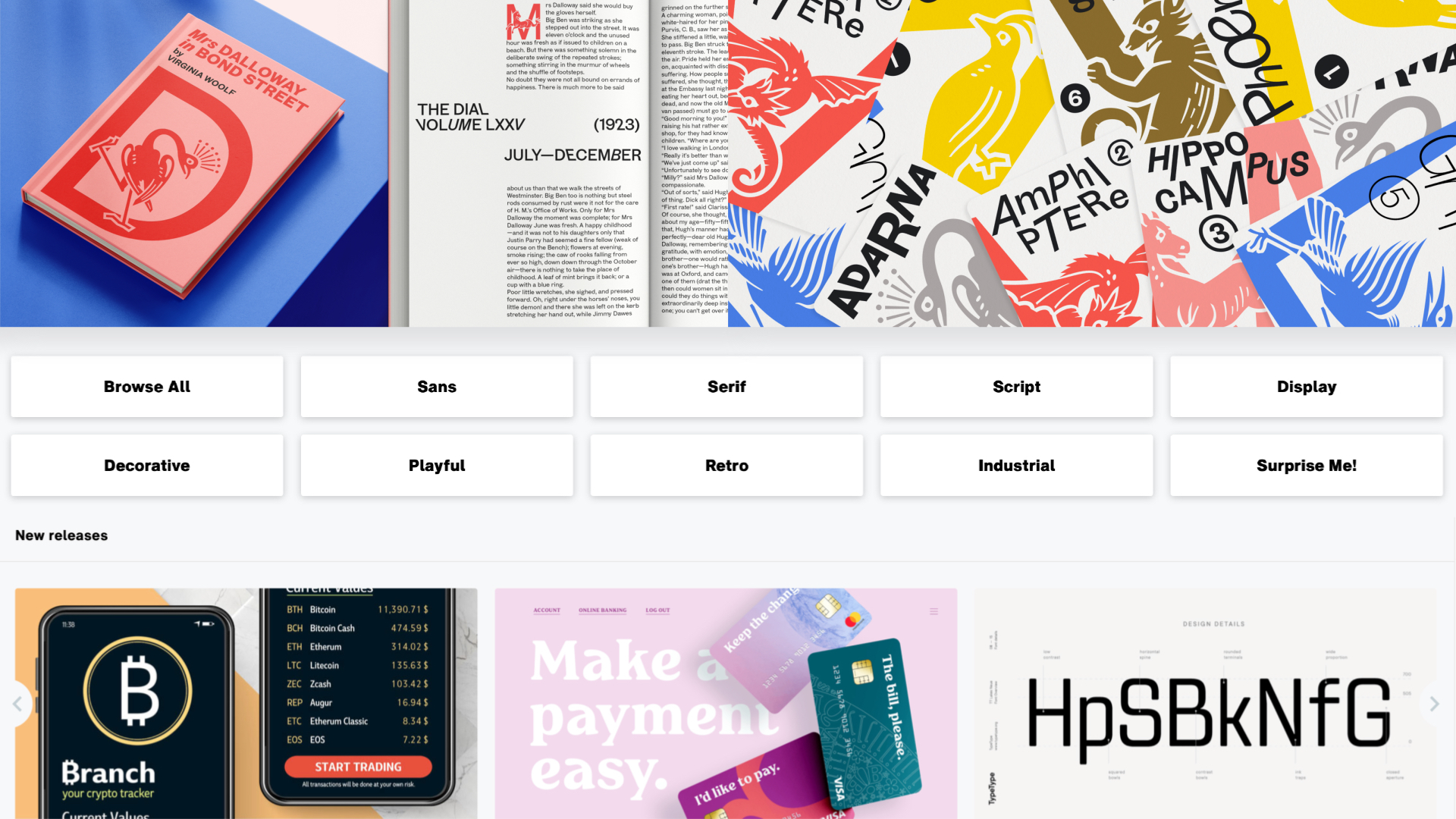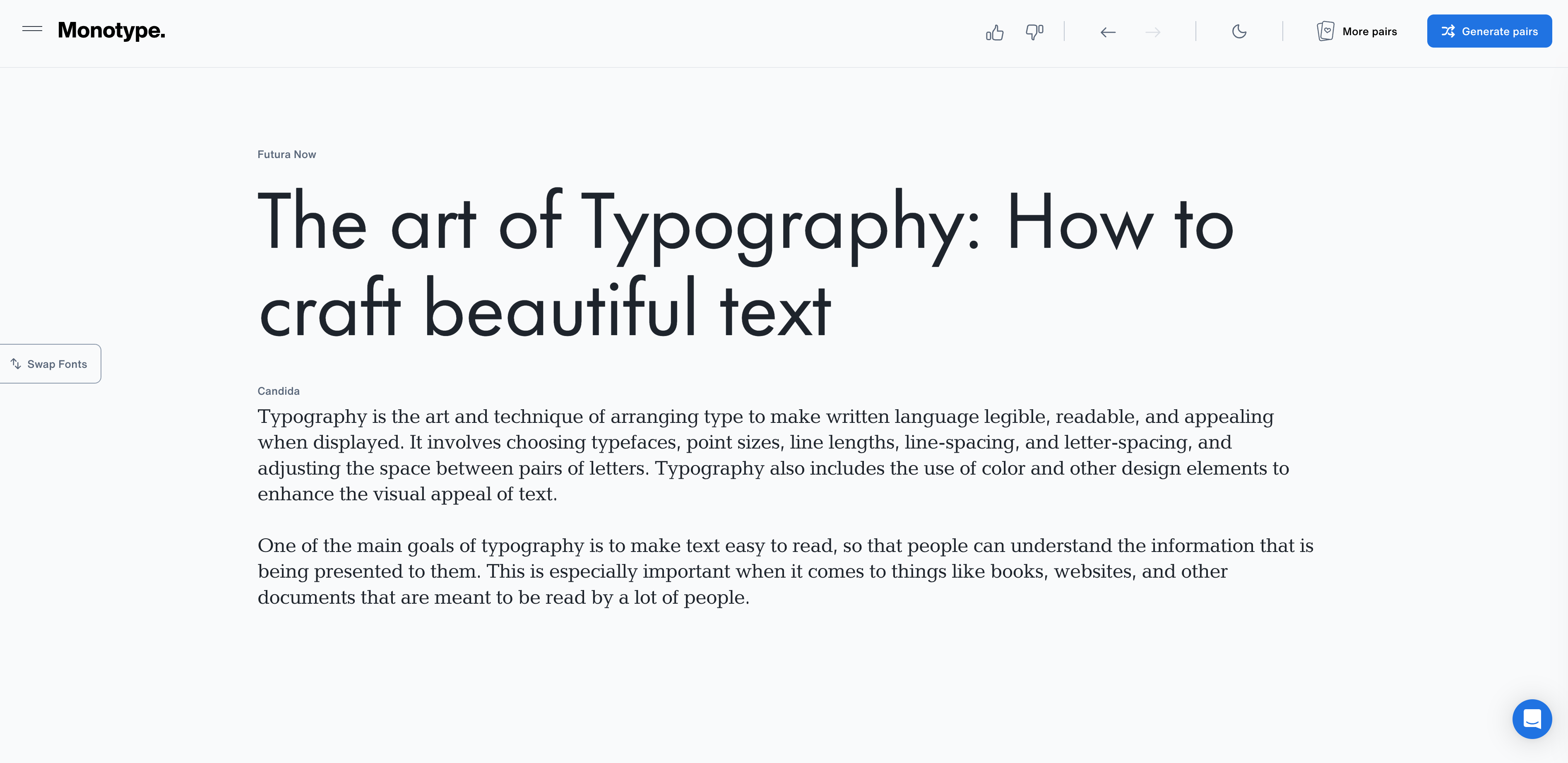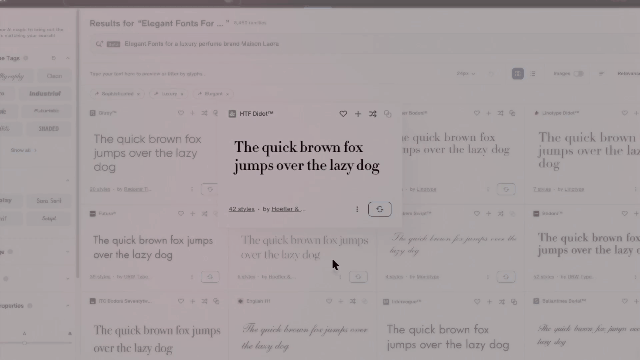
从字形、语言,到文化的边界延展,字体正以更丰富的方式参与品牌构建。近日,《第一财经》对蒙纳全球首席执行官 Ninan Chacko 进行了专访,探讨字体如何影响品牌表达、AI 在字体创作流程中的角色,以及他对付费字体与字体订阅制的深刻见解。
随着 AI 的快速发展,AI 生成工具开始介入字形设计过程,给字体行业带来了新的不确定性。
尽管字体是品牌表达的核心,是品牌视觉识别系统中不可或缺的一环,但其价值往往被品牌所忽视或轻视。版权问题悬而未决,大量非授权使用仍然普遍存在;而免费字体资源与开源平台的流行,也持续压缩商业字体公司的定价空间。
蒙纳字库全球首席执行官 Ninan Chacko 称字体业务为“横向型业务”,它不受地理位置、行业或企业规模的限制,全世界每个地方、每家公司都需要字体,这对字体公司来说是一个巨大的市场。但事实上,字体行业长期面临侵权和大规模盗版的问题,如今 AI 的快速发展也给字体行业带来了新的挑战。
近年来,蒙纳字库尝试从传统的字体销售模式向提供字体管理的整体解决方案转型,在拥有字体设计版权的同时打造字体管理平台。其核心平台 Monotype Fonts 目前拥有超过 25 万款字体,涵盖超过 550 种语言,旨在帮助企业完善字体管理的工作流,包括查找、试用、授权、部署、团队协作等环节。
Ninan Chacko 将 Monotype Fonts 形容为字体行业的 iTunes。这也是他自 2021 年 7 月上任以来主要推动的战略之一,目标是提升字体行业,尤其是字体管理的价值,从而提升蒙纳字库的竞争力。在 Ninan Chacko 看来,以授权形式出售字体失去了设计的独特性、有些“商品化”的味道,授权价格通常较低,并且容易受到侵权,而平台在内容丰富的时代更具价值。
Ninan Chacko 亦坦言,字体设计的耗时长、获得用户反馈的周期长,收购已经成功受到欢迎的经典字体,是扩大字体库并在全球扩张的更高效方式。
Monotype Fonts 平台上的字体搭配 AI 功能
蒙纳字库已经开始尝试将 AI 加入业务环节中,包括字体搜索、字体搭配推荐、加速字体开发等。不过,在 Ninan Chacko 看来,AI 可以帮助优化重复和耗时的环节,但设计的核心依然是人。“就像我不是摄影师,拍照技术也不好。虽然现在的相机技术远远超过 10 年前,但一张好照片仍然需要人的眼光、构图和创造力。没有技术能取代人类独特的艺术触感。” Ninan Chacko 说。
Yi:在如今数字化、全球化不断加速的时代,蒙纳字库的核心使命是否发生了变化?你出任 CEO 以来,有哪些关键的战略转变?
N:我的背景并不来自字体、设计或创意经济。我是航空航天工程师出身,职业生涯曾涉足媒体、出版、旅游和科技等多个行业。我的目标并不是要成为公司里最具创意的人,我的职责是制定一个战略,使蒙纳字库和整个字体行业在未来具备更强的竞争力。
我加入蒙纳字库时,字体行业面临着一定的“商品化”风险,我的战略方向就是要提升整个行业的价值感,特别是关于“字体管理”的价值定位。用音乐行业来打比方或许能更好地说明我们正在经历的变化。25 年前,音乐是以永久授权的形式销售的,你买了一张 CD 或黑胶唱片,就永久拥有它;后来进入 MP3 时代,盗版、病毒等乱象丛生;再后来,音乐行业迈入了流媒体时代。
一开始,我也不确定流媒体是否会成为主流,但如今,它无疑已经主导整个音乐市场。流媒体带来了丰富的内容:无穷无尽的音乐,随时随地可以播放,几乎没有任何使用门槛。平台还能通过算法收集你的偏好,提供个性化推荐。在这个过程中,音乐行业的价值从曲库逐渐转移到了平台,今天,Spotify 或 iTunes 的平台价值已经超过了音乐内容本身。
字体行业也在经历类似的演变。过去,字体是以永久授权形式出售的,通过 CD-ROM 等物理媒介分发,有些“商品化”的味道,价格也较低。蒙纳字库拥有世界上很多流行字体的版权,但我们没有止步于“拥有”字体,我们打造了一个软件平台 Monotype Fonts,希望帮助企业完整管理字体工作流,包括查找、试用、授权、部署、协作等所有环节。我们的自有字体库包含约 5 万款字体,还有来自第三方字体公司的 25 万至 30 万款字体,他们选择通过我们的平台进行销售。这就像亚马逊模式,除了自营商品,还有很多第三方卖家。
我们的战略核心是:不再把字体本身当作产品销售,而是提供字体管理的整体解决方案。归根结底,字体是品牌的具象化表达。品牌要说什么、怎么说,全靠字体传达。如何在全球范围内持续、统一地管理字体资产,是所有品牌都非常在意的问题,而我们正在帮助他们解决这个问题。
Yi:你曾将Monotype Fonts形容为字体行业的 iTunes。它能否更好地应对字体行业所面临的冲击?
N:我认为是可以的。如果你观察当今各行各业的创新趋势,你会发现一个共同点:丰富。无论是流媒体平台、新闻行业,还是电商平台,人们都期望拥有无限的选择权、灵活性,以及随时随地消费内容的自由。而我们希望把这种丰富性和可及性带入字体世界。如果只有 50 款字体,你大概还能记得他们的名字,搜索起来也不难;但当有 40 万款字体时,就必须依靠更强大的搜索与推荐工具。
我们也在提升字体搜索和发现的体验。你不需要记住字体的名字、公司,或者用专业术语去形容它,你可以直接用自然语言来表达,比如:“我正在为一部发生在凯撒时代罗马的电影设计片尾字幕,有哪些字体能传达这种氛围?”我们希望平台能理解这样的问题,并给出推荐,AI 正在帮我们实现这一目标。在我看来,这是真正的“字体民主化”:提升上限、降低门槛,让更多人可以接触字体,并高效地加以使用。
当然,任何商业策略都有挑战和机遇 。与以往的模式相比,有一些人希望字体继续作为字体专家的专属领域。当行业发生变化时,有更多人可以接触到同样的资源,也总有人会觉得自己的专业知识被削弱了。
Yi:近年来,蒙纳字库在全球范围内进行了一系列收购和区域拓展。这背后的主要考量是什么?
N:还是回归到我们的初衷:成为真正的字体全领域领导者 。我们希望拥有更多的字体资源,不仅是拉丁字体,还包括中文(简体和繁体)、日文、韩文、印度文、希伯来文、阿拉伯文等等。如果这些字体全部由我们自己来开发,耗时将非常长,可能利用 AI 会稍微快一点儿。
字体设计有点儿像拍电影,你不能确定它是否会成功。你可能觉得请到了好的演员、剧情也不错,但电影上映后观众并不买单。字体也是一样,你设计出漂亮的字体,但要到几年后才能知道大家是否喜欢。通过收购字体,我们能够引入那些已经成功的经典字体,尤其是非拉丁文字体,他们经过了时间的考验,依然受到欢迎。最流行的字体不会每周变动,甚至 10 年都不会有太大变化。收购字体公司和与第三方字体公司合作,是我们扩大字体库的高效方式。
至于我们在首尔、巴黎、日本等地设立办事处,是为了更好地服务各地市场。教育市场和深耕市场的最好方式,是在当地派遣具备相应技能和知识的团队。以中国为例,刚开始时中国团队只有 8 到 9 人,而现在已经超过 30 人。拥有本地同事,能够理解语言、文化和商业环境至关重要。
Yi:目前,全球字体市场的增长情况如何?
N:我认为全球字体市场仍在稳步增长。我们曾与一家外部咨询公司合作,估算目前的市场规模接近 100 亿美元,并且每年都在持续增长。
过去 5 年,一个重要的转折点是疫情,它带来了数字化投资的浪潮。而每一轮新技术的浪潮,都会给字体行业带来更多机会。因为疫情大家都待在家里,无法前往线下门店,因此无论是在淘宝还是在亚马逊上,品牌都在加大对线上形象的投入。而在数字世界中,品牌之间的差异化很难通过实物体现出来,品牌形象就显得格外重要,而字体正是品牌表达自我最核心的方式之一。
另一个趋势是个性化。一个网站或 APP 的视觉风格,往往通过字体来体现。即使我们用同一款手机,我们的界面也因为字体的不同而呈现出不同的风格。随着手机、手表等越来越多的显示设备出现,字体必须能在各种环境中良好呈现,从巨大的户外广告到手表上的小屏幕,字体不仅要好看,还要清晰、统一、可靠。
此外,随着网络诈骗活动增多,用户对于品牌的视觉呈现也更加敏感,字体的选择在品牌可信度方面变得更加关键。尤其对于迪士尼、宝洁等高度重视品牌一致性的公司而言,字体就是品牌表达中不可或缺的一环,他们为此投入了数亿、甚至数十亿美元。
所有这些趋势都助推了字体市场的增长。作为行业中的主要玩家之一,我们也因此受益。放眼未来,当增强现实和虚拟现实等技术真正落地时,对高分辨率和清晰显示的需求也会大幅提升。而这正是字体发挥作用的地方 —— 因为字体就是让技术视觉呈现得更清晰、更锐利的软件基础。
Yi:但在中国,很多新兴品牌似乎并不太重视字体设计。你怎么看待这个现象?
N:我认为品牌在起步阶段确实可能如此,但如果我们看当今最成功的中国企业,他们几乎都在走向国际化,需要打造具有全球影响力的品牌。品牌表现的一致性和可信度是所有国际品牌都需要解决的问题。
新兴品牌在起步阶段可能比较“草根”,用的是本地解决方案或免费字体,但随着企业的发展,就像人长大了穿衣风格会变化一样,他们也开始用更成熟的方式展现自己,这是一个自然的演变过程。
那些最值得尊敬和欣赏的企业有一个共同点,就是他们对品牌的高度重视。这些品牌往往具有强烈的标识性和辨识度。我们有时会做一个实验:把一些知名品牌的颜色和标志去掉,只留下文字内容,人们可能不知道字体的名字,但立刻能判断出它代表的是哪个品牌。这说明字体的力量是潜移默化的。
用不同字体设计的品牌标识首字母,具有明显的品牌识别性。
Yi:亚洲市场,尤其是中国市场,在蒙纳字库的全球战略中扮演着怎样的角色?相比于西方市场,你们在亚洲看到了哪些独特的机遇与挑战?
N:我们之所以选择在亚洲,尤其是在中国发展,是因为这里的市场规模巨大。中国拥有超过 10 亿人口,同时正爆发着大量新兴企业,拥有庞大的用户群体,几乎是全球最大的市场,仅有印度可以媲美,而我们希望能够处在这一增长的中心。
我们面临的最重要挑战之一,是我们的中文字库的广度仍不如西文字库。我们正在持续投入扩大中文字体资源,同时,我们也在不断扩大本地团队 —— 目前主要聚焦于上海、北京、广州和深圳。另一项重点工作是对 Monotype Fonts 的本地化改造,这个平台目前还没有完全适配中国市场,我们正着手进行语言支持、内容供应等方面的优化。
Yi:你刚才提到,在数字化时代,字体设计变得越来越重要。那么数字化转型带来了哪些新的字体需求或趋势?
N:除了我之前提到的一些趋势,目前还不完全清楚 AI、增强现实、虚拟现实等技术会在多大程度上改变字体的功能。但我确定的是,这些技术会增加对字体设计的需求。例如,流媒体内容的爆发式增长带来了对字幕等场景下字体的巨大需求 ,特别是字幕,因为流媒体的用户来自世界各地,需要各种语言的字幕。Netflix 就是我们的客户,我们帮助他们优化字幕的字体,确保其清晰易读。这说明内容量、选择和个性化的爆发式增长可以推动字体市场的发展,我相信这种趋势会持续。
另外,免费字库意味着任何人都可以用同样的字体,街角的洗衣店可能和你用的是同一款字体。如果你想要真正独特、能体现品牌个性和承诺的字体,比如 Frutiger 这样的经典字体,这不是免费字体可以提供的,而这正是我们的核心价值所在。
Canva 用户使用蒙纳及其合作字体厂商提供的字体,已创作超过 10 亿件设计作品。
Yi:你如何看待当前全球字体行业的发展状况?你认为字体行业未来最重要的发展趋势是什么?
N:我认为字体行业仍然是一个非常丰富的生态系统。如果你从世界上一些知名的字体设计课程毕业,比如雷丁大学、巴塞尔或纽约帕森斯设计学院,毕业第二天你就可以创办自己的字库。有趣的是,现在有越来越多热爱字体的人投入这个行业,创立新的字体工作室,设计新的字体。虽然竞争非常激烈,但看到这么多人投身其中是一件很令人振奋的事。
我尤其对一些新兴地区的字体发展感到着迷。比如印尼,它已经成为全球最活跃的字体市场之一,字库数量和字体产出量都可以排进全球前十。巴西的字体设计行业也很活跃。这正是这个行业迷人的地方:生态系统多元而充满活力,而且还在持续增长。字体本质上是表达的一种形式,而我相信人类永远不会停止表达自我。所以我对这个行业的未来充满信心,它会持续成长、不断创新,充满活力。